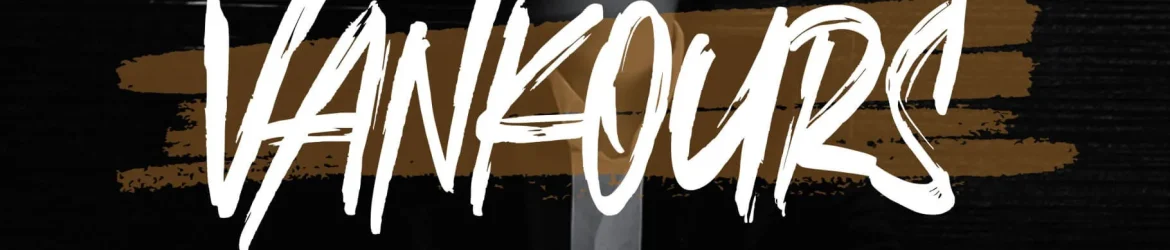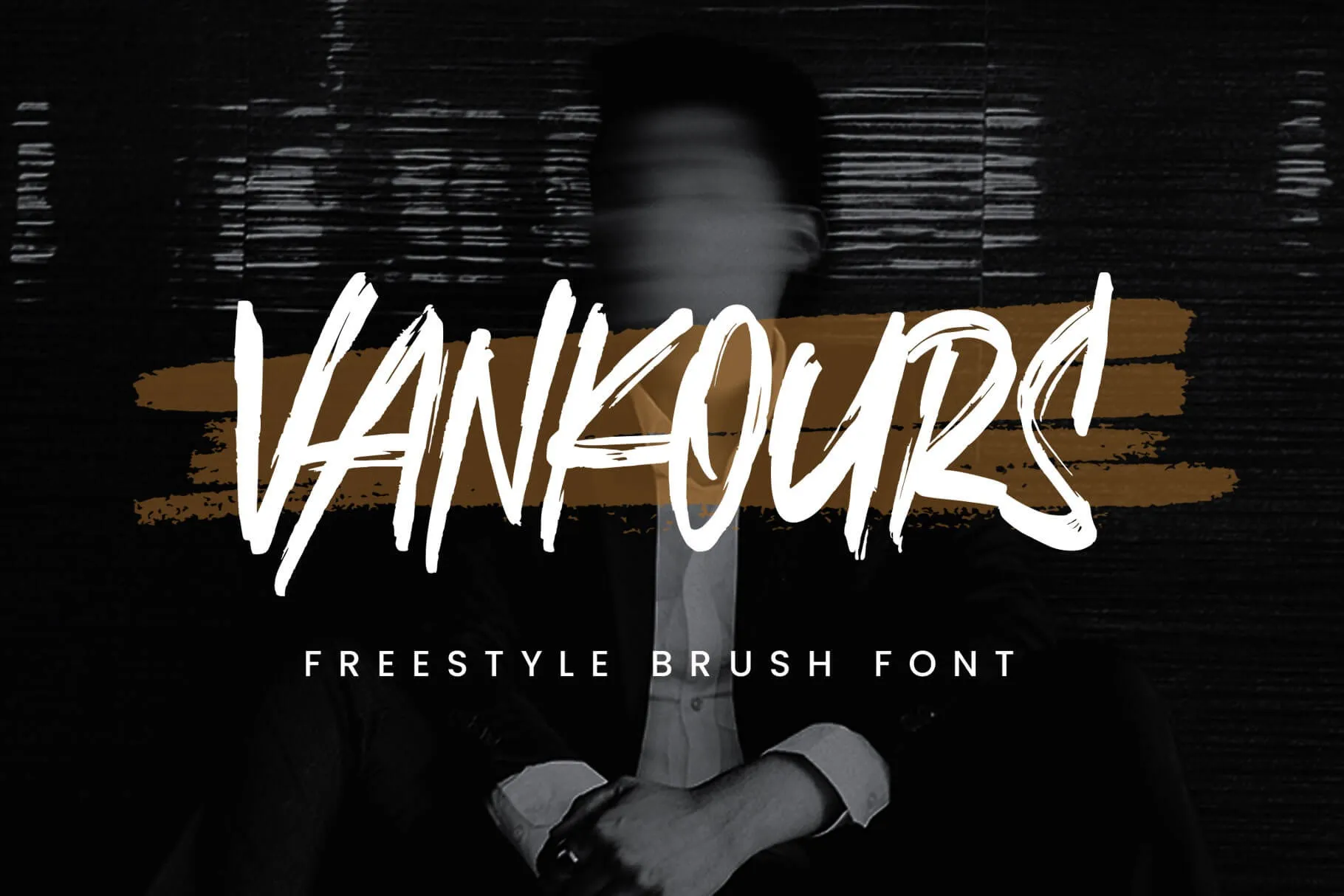
Vankours Font – Fonte Grátis
Vankours Font
A fonte ‘Vankours’ oferece uma experiência autêntica e vibrante para projetistas digitais no Brasil e em outros lugares do mundo. Com suas linhas finas e robustas, cada caractere desta fonte é resultante de um processo manual meticuloso feito com esmero por um artesão da letra, utilizando pincel e tinta a base de água de alta qualidade. Essa fonte se destaca perfeitamente para vários temas, incluindo urbanidade, thriller, atletismo, vitalidade e paixão juvenil. Ela é uma escolha perfeita para criar logos, produtos merchandising, imagens de marca, roupas, embalagens, simples citações, entre muitos outros usos possíveis. Para quem procura um estilo único que se destaca em projetos visuais, a ‘Vankours Font’ é uma ótima opção. Seja você um designer de logomarcas, uma empresa buscando uma identidade visual única ou até mesmo aquele amante dos detalhes que quer trazer vida para suas produções digitais, ‘Vankours’ tem o poder de transformar qualquer projeto no qual esteja inserido em algo que se destaca.